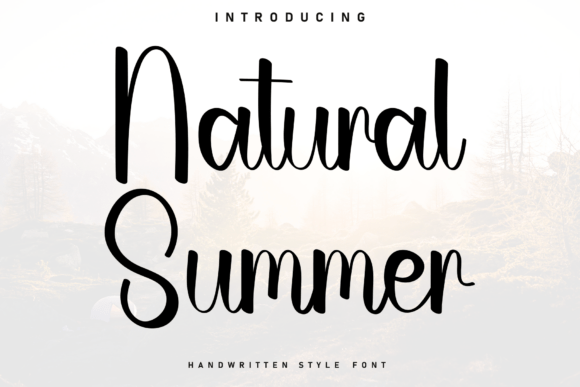
Natural Summer
適切なデザイン要素を見つけるのは難しい場合がありますが、Natural Summerは作品を即座に引き立てる優れたコレクションを提供します。
POD(オンデマンド印刷)製品、結婚式の招待状、またはソーシャルメディアのグラフィックを作成している場合でも、Natural Summerは理想的です。